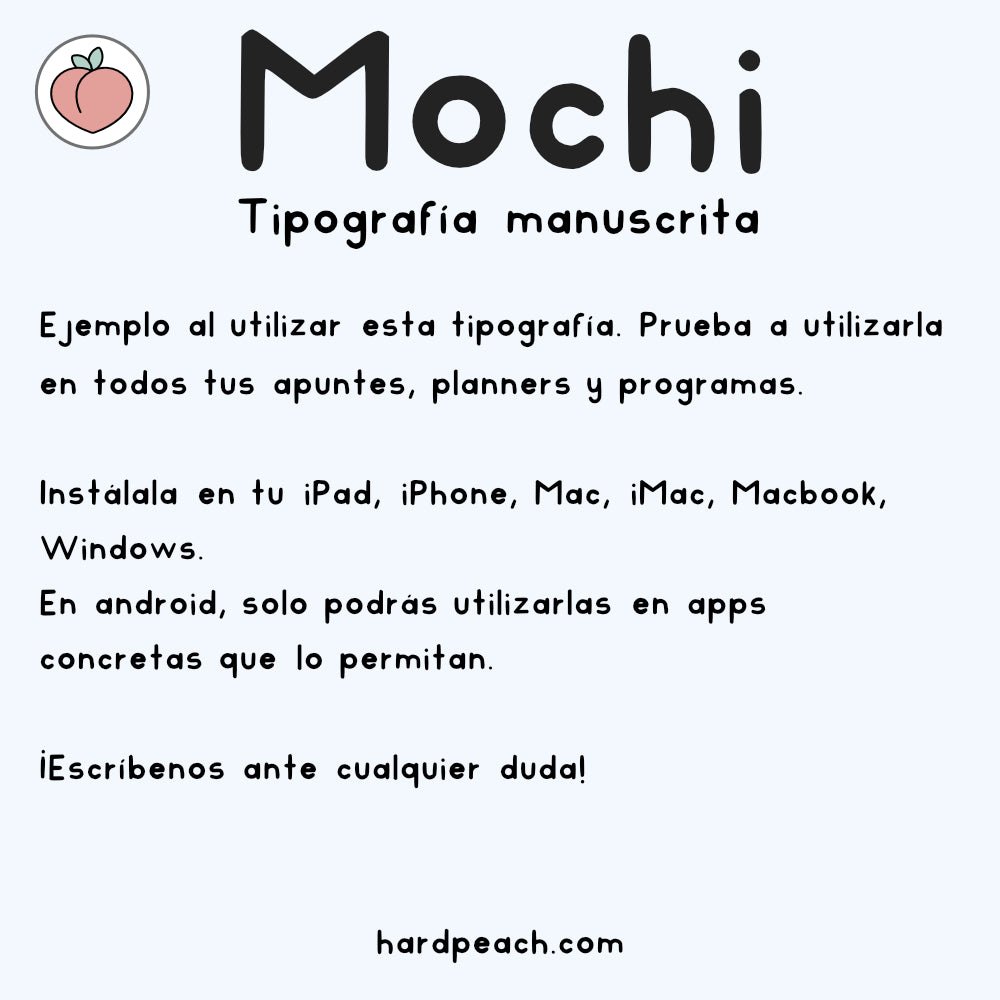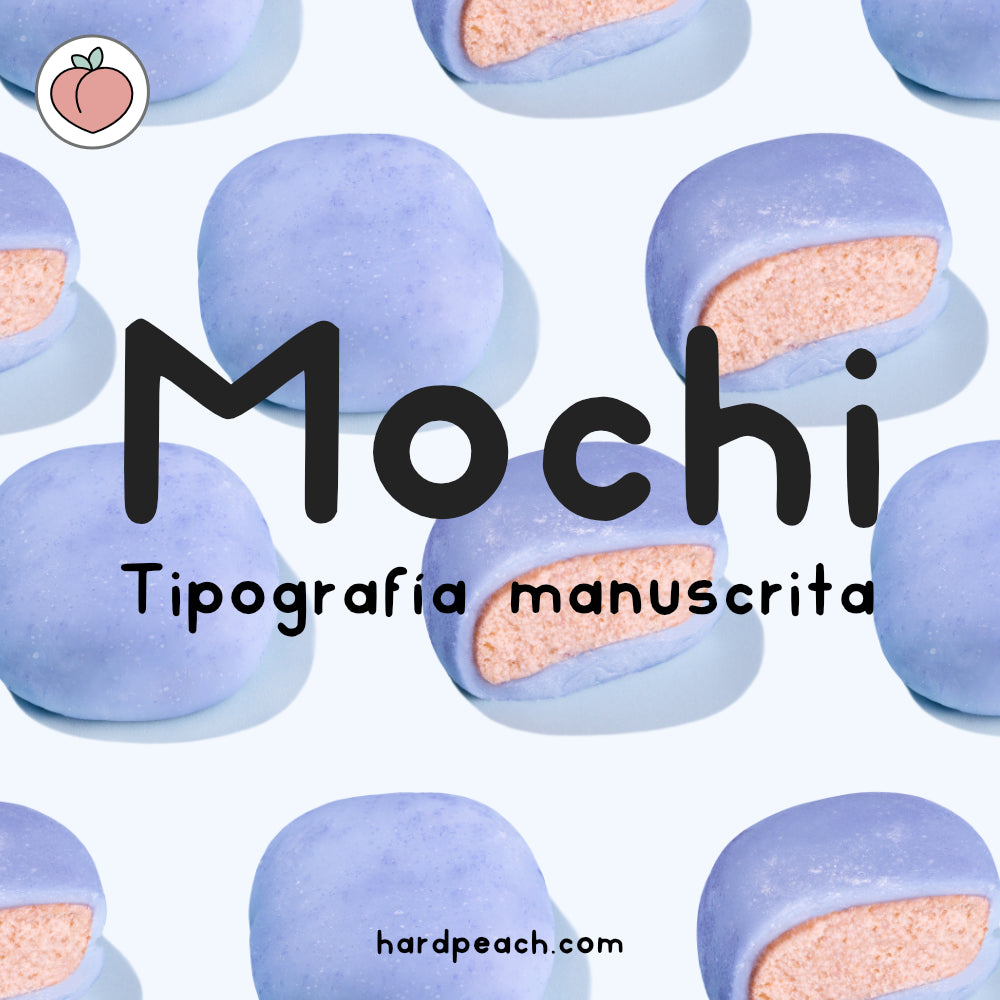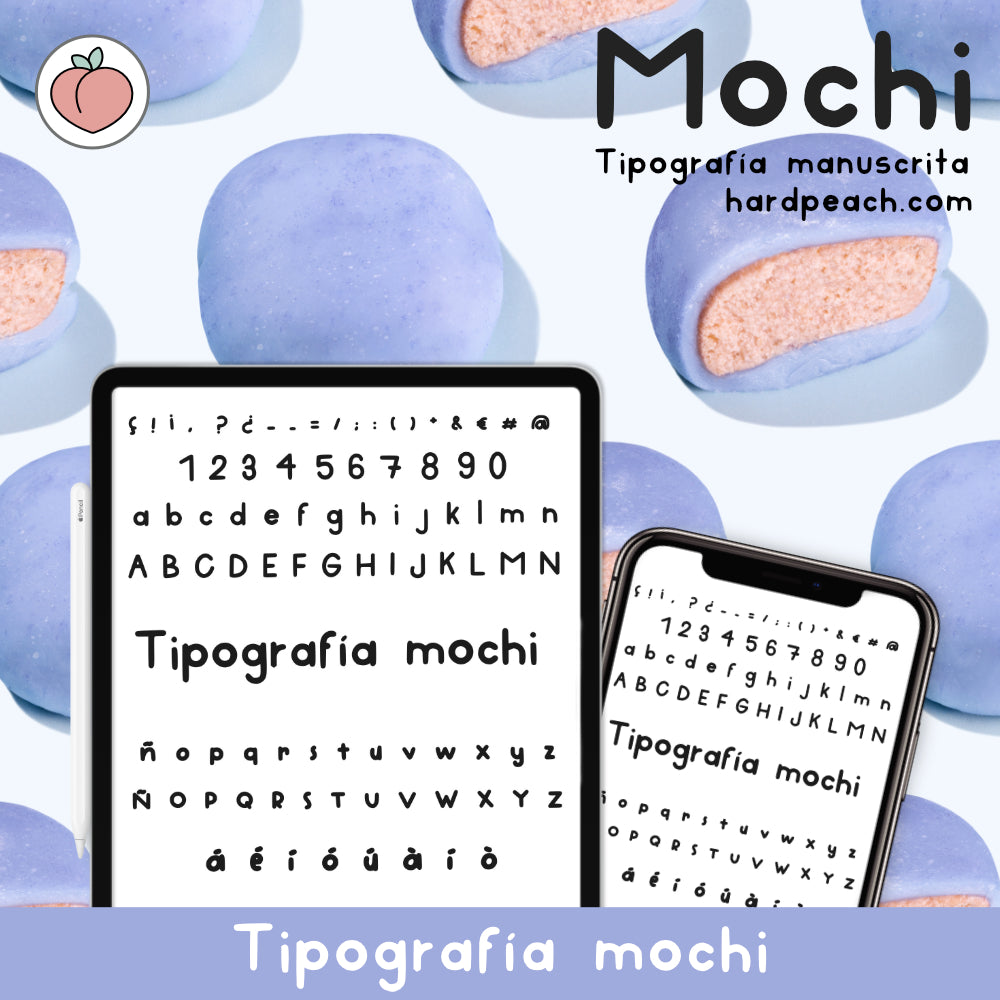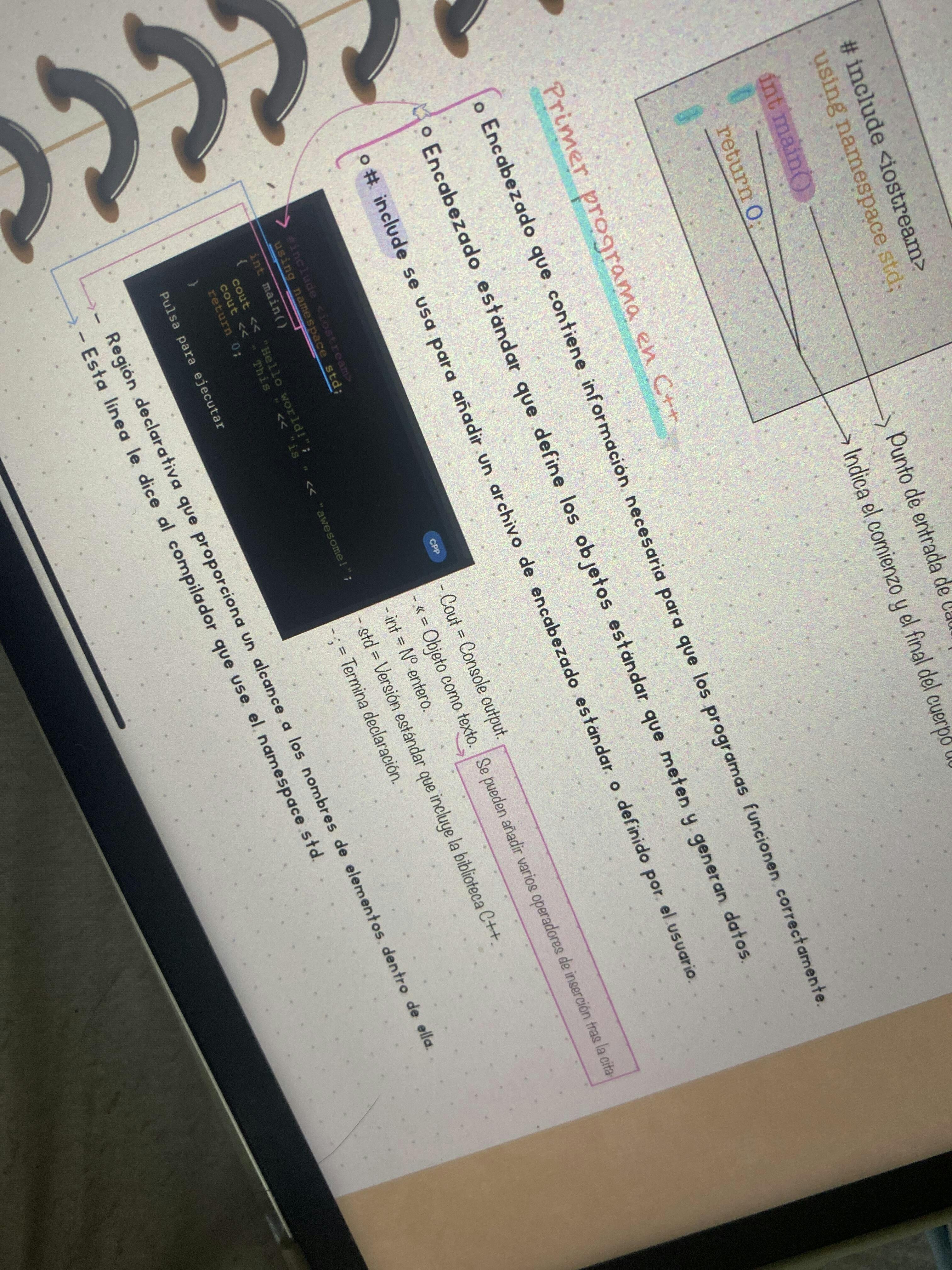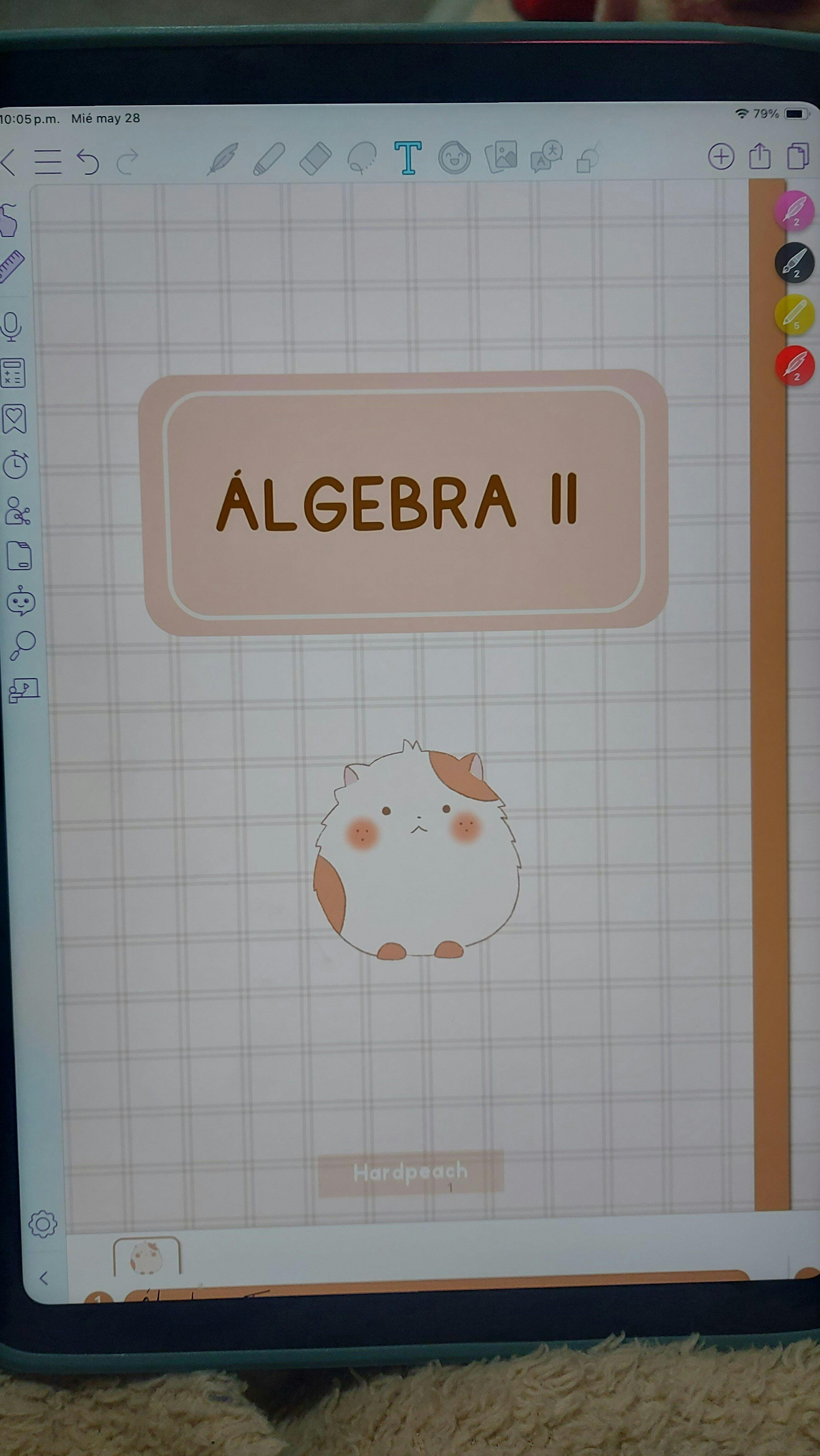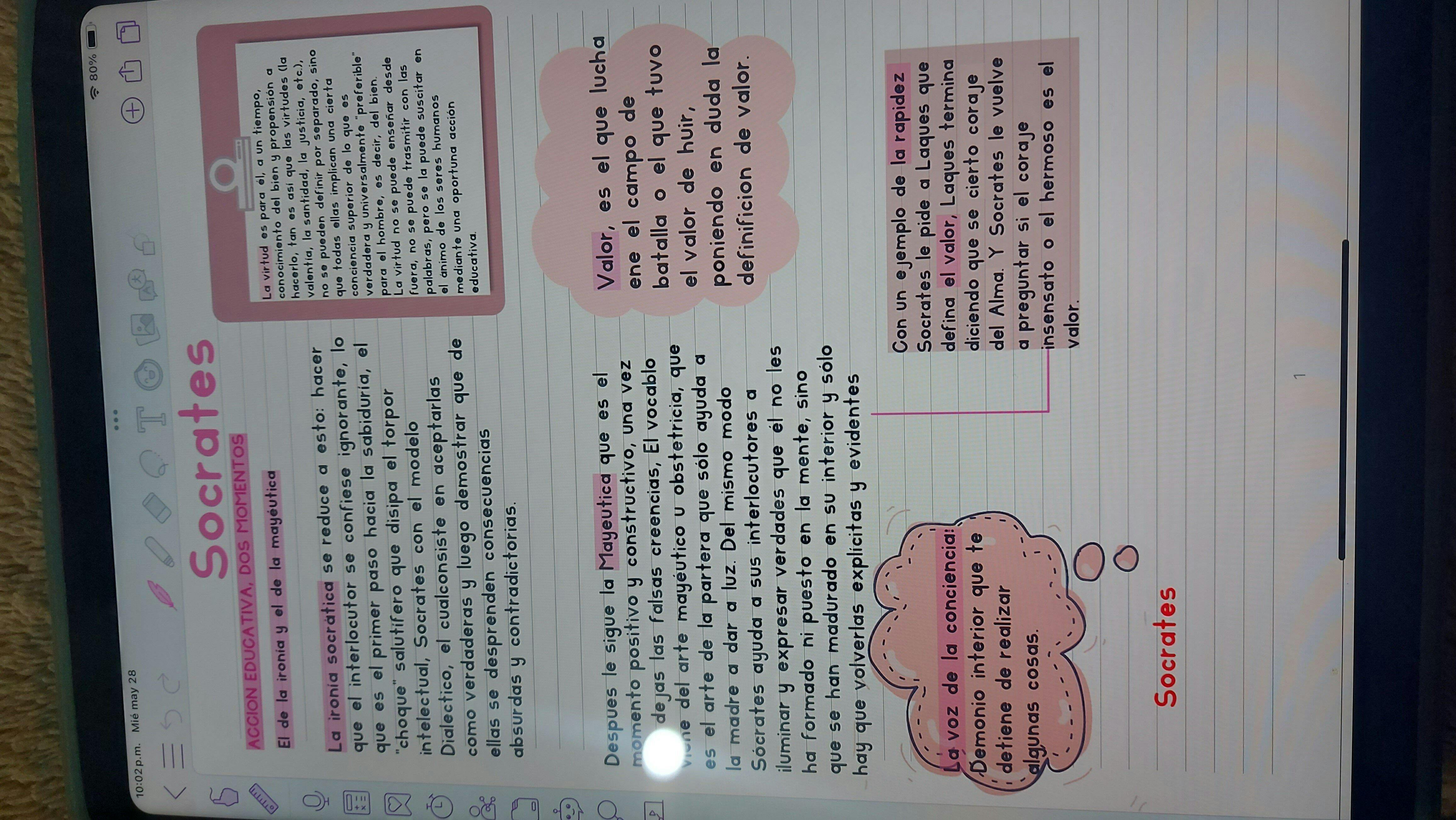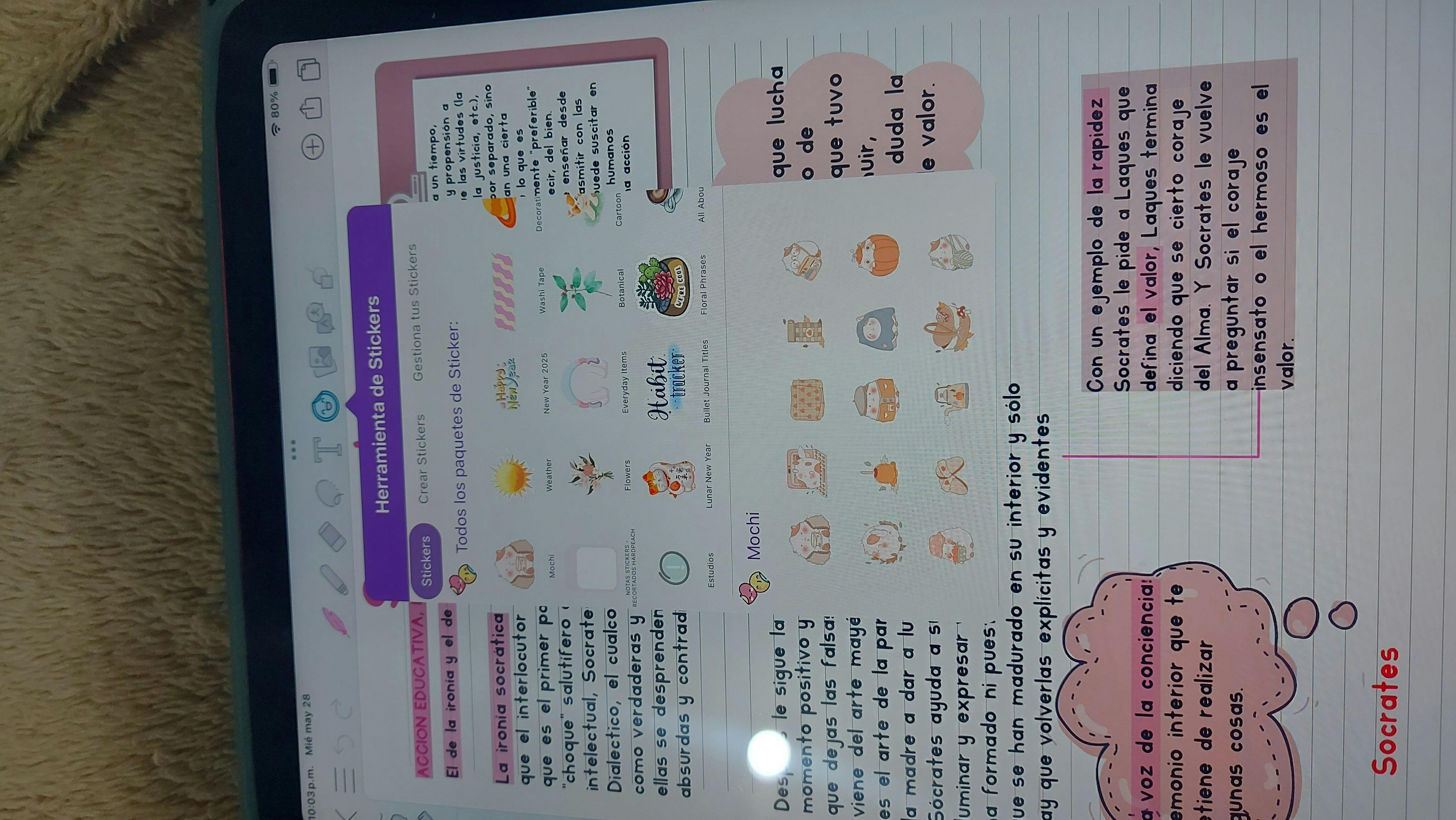
TIPOGRAFÍA MANUSCRITA MOCHI | FUENTE ESCRITA A MANO
Descubre esta tipografía manuscrita Mochi perfecta para todos tus apuntes digitales, notas, esquemas y proyectos creativos. Su diseño fluido y natural la hace ideal para redacción de textos en apps y programas. Dale un toque personal y único a tus apuntes, documentos, presentaciones o proyectos digitales.
Esta tipografía es perfecta para:
- Apuntes digitales y para imprimir📝
- Anotaciones rápidas y esquemas organizativos 📚
- Títulos elegantes para documentos y presentaciones ✨
- Bullet journals, agendas y diarios creativos 🎨
- Proyectos de ilustración, diseño gráfico y lettering digital 🖌️
- Esquemas, diagramas y organización de ideas 📝
Esta tipografía incluye todos los caracteres principales: mayúsculas, minúsculas, números, vocales con tildes cerradas y abiertas, signos de puntuación y la letra especial Ç, para que puedas escribir con total libertad y sin límites.